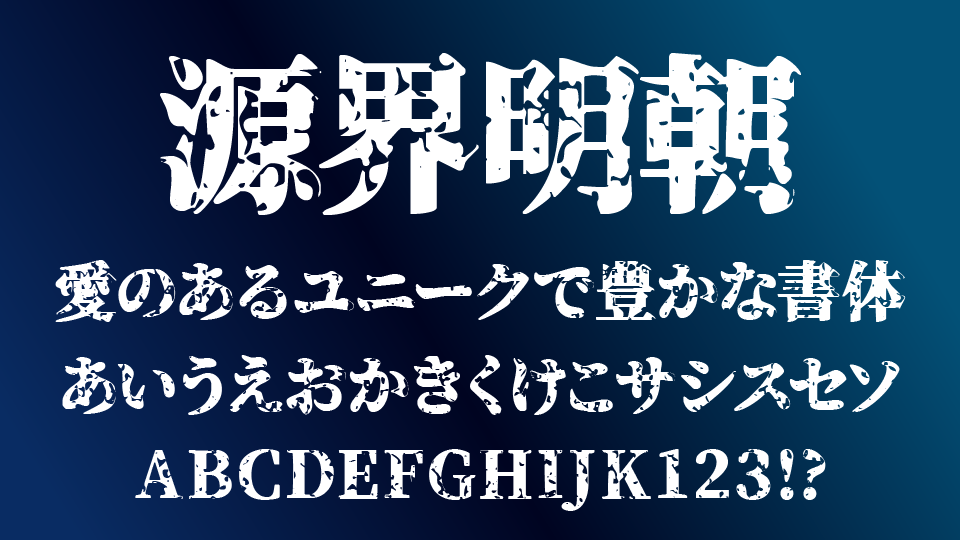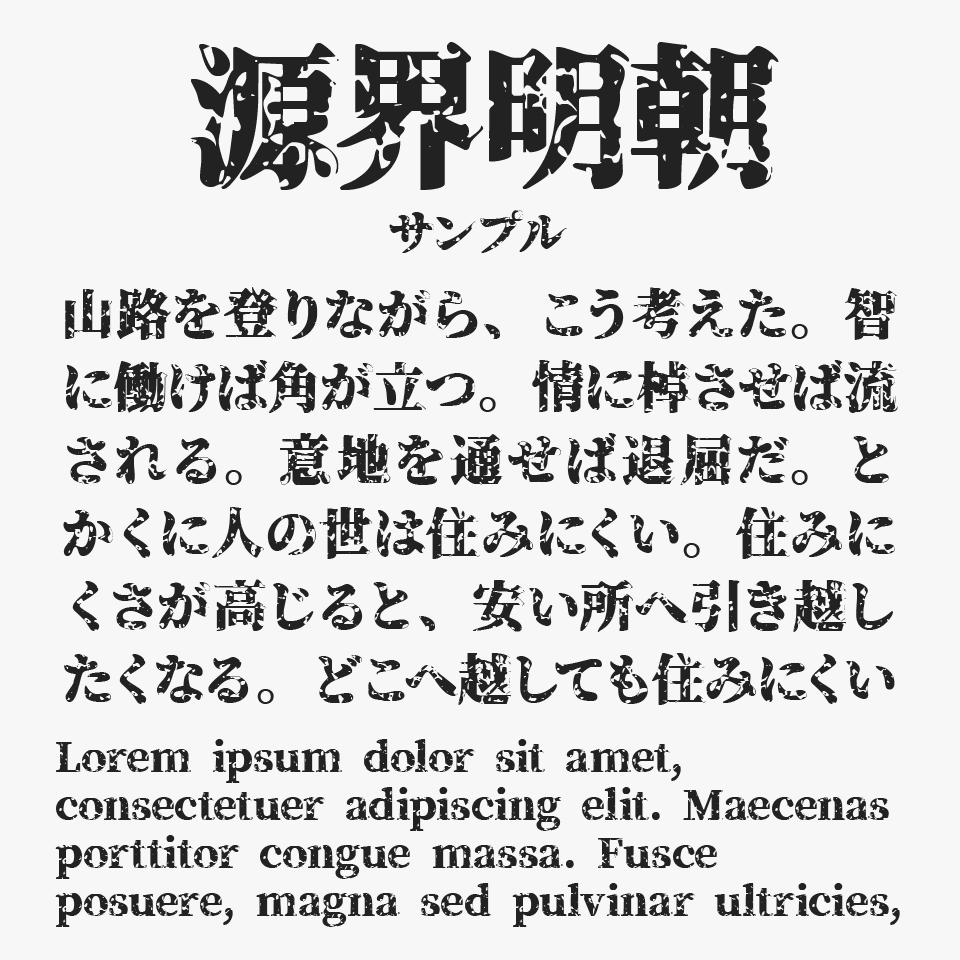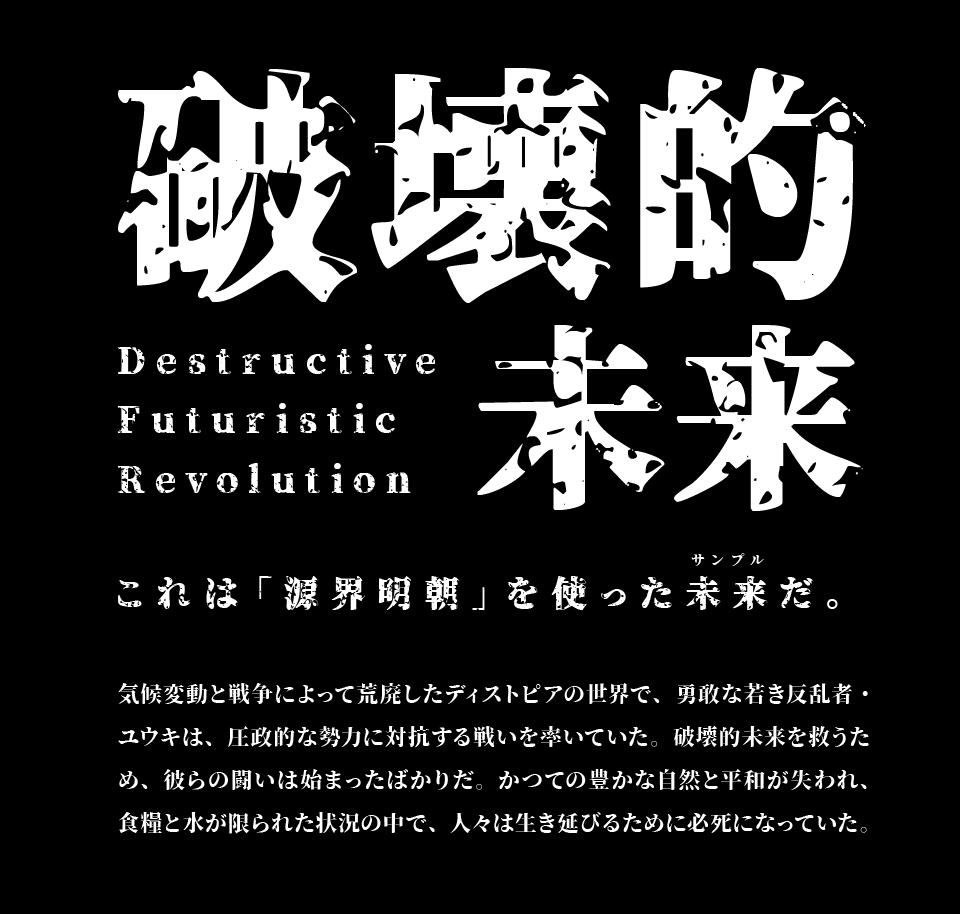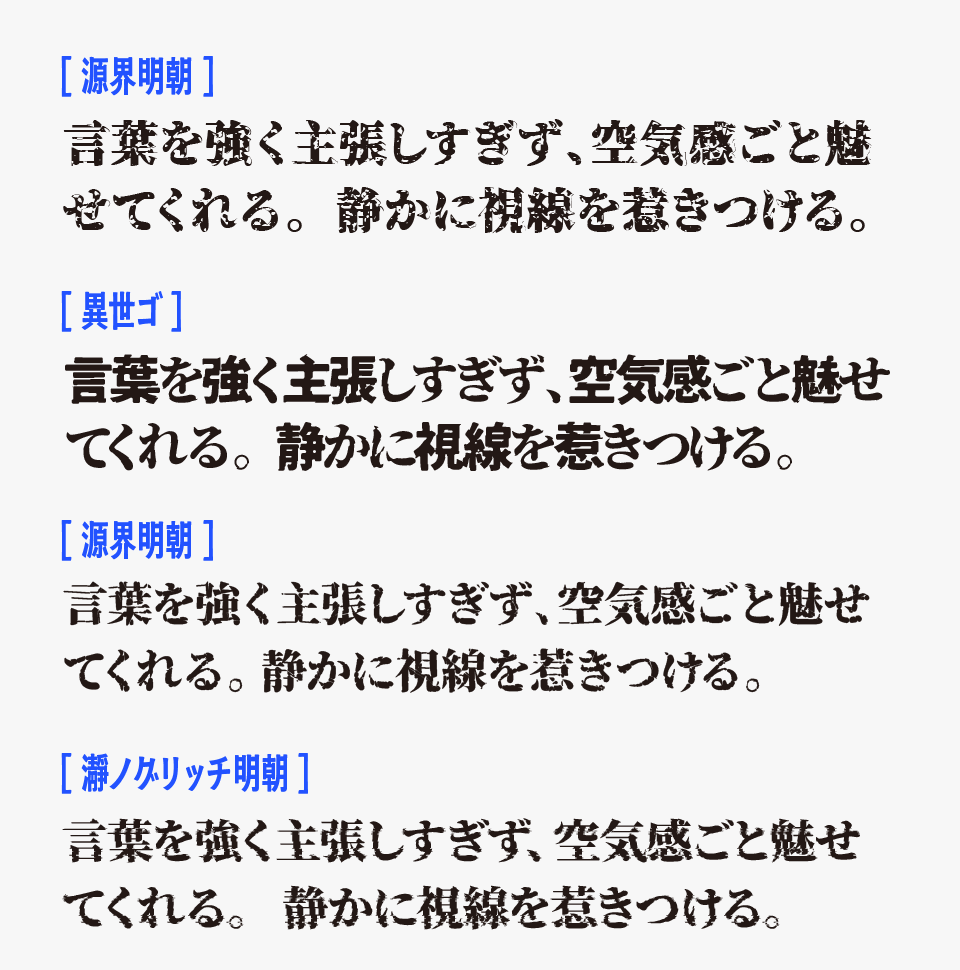
源界明朝
源界明朝フォントは、源ノ明朝をベースに“読める限界ギリギリ”まで大胆に破壊されたような、強烈なかすれ・グランジ加工が施された明朝体フォントです。
文字の輪郭には擦れや欠け、崩れたような加工が加えられており、まるで古びた印刷物やノイズ混じりの映像のような、退廃的で不穏な空気感があります。普通の明朝体にはない荒々しさがあり、一文字だけでも強い存在感を放つインパクトあるデザインになっています。
可読性はギリギリ保ちながらも、あえて崩した絶妙なバランスになっているため、タイトルや見出し、MV風デザイン、ホラー・サブカル・ダーク系ビジュアルなどとも相性抜群です。文字を打つだけで“世界観”を作れる、非常に個性的な明朝体フォントとなっています。
このフォントは「破壊された世界」をテーマにして制作されているので、同人やアニメ・マンガなどのタイトルロゴや見出しデザインなどと相性がとても良いです。
簡単にベタ打ちしただけですが、とっても簡単に「それっぽい」タイトルデザインを作り出すことが可能なとってもステキなフォントです。
源界明朝を、同じようにグランジ表現を取り入れたフォントと比較してみると、“破壊感”の強さと文字の限界ギリギリを攻めた加工表現が特に印象的です。
比較フォントは、「異世ゴ」「源界明朝」「瀞ノグリッチ明朝」と使用していますが、どのフォントも独特な質感がステキなので、あわせてチェックしてみてください。
収録文字は、ひらがな・かたかな・漢字・アルファベットには一通り対応しています。(源ノ明朝 に基づいた収録文字)